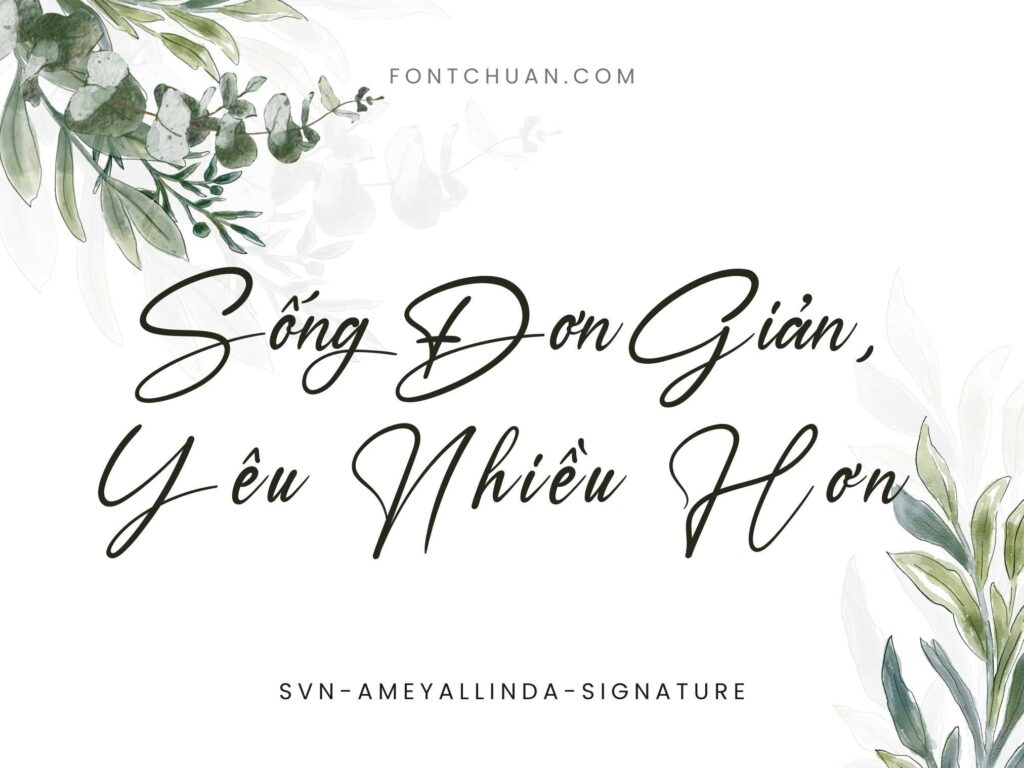
Font SVN Ameyallinda Signature Việt Hóa
Tác giả Font: Scratchones
Ameyallinda Signature là một font chữ viết tay hiện đại, được thiết kế bởi Scratchones Creative. Font này mang phong cách thanh lịch và tinh tế, phù hợp cho nhiều mục đích sử dụng như thiệp mời cưới, logo, bài đăng trên mạng xã hội, quảng cáo, bao bì sản phẩm, thiết kế nhãn mác và nhiều dự án sáng tạo khác. Với bộ ký tự đầy đủ bao gồm chữ hoa, chữ thường, số, dấu câu và các ligature, Ameyallinda Signature cung cấp sự linh hoạt cho các nhà thiết kế trong việc tạo ra những tác phẩm độc đáo. Font đã được Việt hóa để hỗ trợ tiếng Việt bởi Styleno.1 Fonts, đồng thời hỗ trợ nhiều ngôn ngữ khác, giúp mở rộng phạm vi sử dụng trên toàn cầu. Font này được thành viên của Font Chuẩn sưu tầm và chia sẻ, đáp ứng nhu cầu của bạn đọc và ứng dụng thực tế vào các dự án thiết kế.
Đặc điểm thiết kế của Ameyallinda Signature bao gồm các đường nét mềm mại, uyển chuyển và tự nhiên, tạo cảm giác như chữ viết tay thực sự. Font này phù hợp cho các ứng dụng như thiết kế thiệp mời, tiêu đề, logo, nhãn hiệu và các sản phẩm quảng cáo. Các ngành nghề phù hợp bao gồm quảng cáo, sự kiện, thời trang, làm đẹp và nghệ thuật.